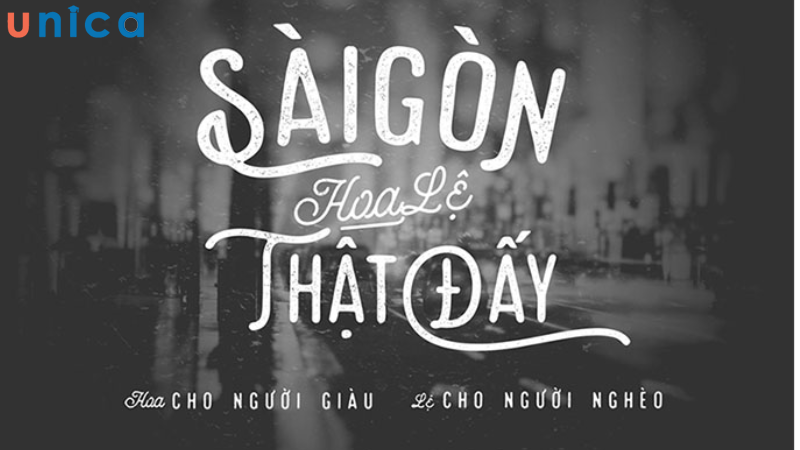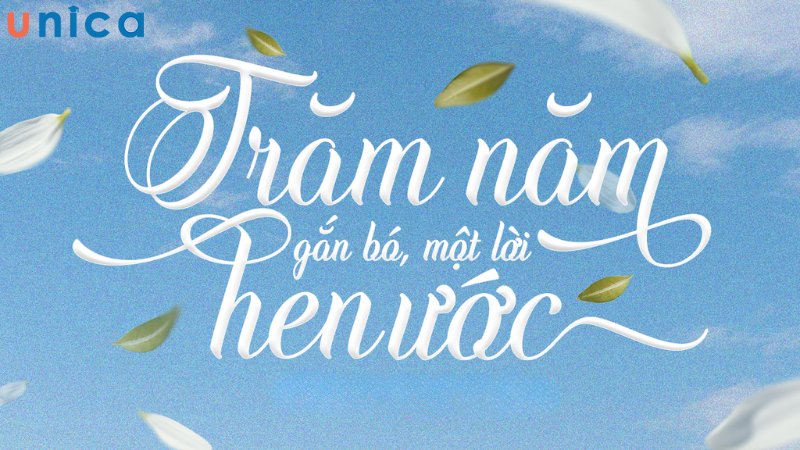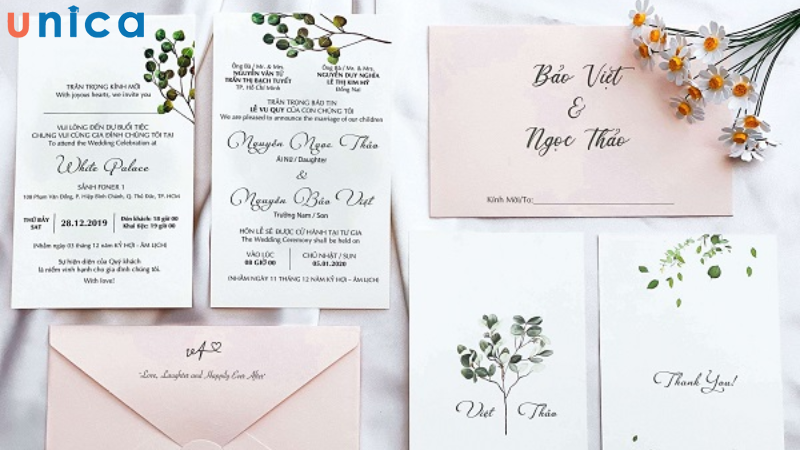
Top 30+ Font chữ viết tay Việt hóa cho người làm thiết kế
Việc sử dụng các font mặc định để viết chữ trong phần mềm Photoshop sẽ làm cho những designer bị gò bó và thiếu đi sự sáng tạo. Vậy làm thế nào để các designer có thể tự tạo nên những Font chữ Việt hóa theo mong muốn của mình. Sau đây, Unica sẽ gửi đến các bạn Top 5 Font chữ viết tay Việt hóa đẹp nhất mà không phải ai cũng biết.
Font chữ việt hóa viết tay là gì?
Font chữ viết tay Việt hóa là những bộ font đã được điều chỉnh và tối ưu hóa để hỗ trợ đầy đủ các ký tự trong tiếng Việt. Những bộ font này thường được sử dụng trong các thiết kế đồ họa như thiệp mời, thiệp chúc mừng, hay các ấn phẩm quảng cáo. Việc sử dụng các font viết tay giúp thay đổi diện mạo thiết kế, mang đến nét độc đáo và sự khác biệt nhờ vào sự đa dạng của các kiểu chữ.
Font chữ viết tay mang đến nhiều lợi ích thiết thực cho người dùng, đặc biệt trong các hoạt động sáng tạo và thiết kế. So với việc sử dụng các font chữ thông thường, bộ font này không chỉ đa dạng hơn mà còn truyền tải được cảm xúc và phong cách riêng biệt.
Font chữ viết tay Việt hóa là những font chữ đã được tối ưu khi soạn thảo bằng tiếng Việt
Về cơ bản, font chữ viết tay (hay còn gọi là Typography) là các kiểu chữ được hiển thị trên màn hình máy tính theo phong cách viết tay tự nhiên. Một số bộ font được Việt hóa hoàn chỉnh để phù hợp với tiếng Việt, trong khi các bộ khác được tạo ra theo phong cách nghệ thuật, mang đậm dấu ấn thiết kế.
Những bộ font chữ viết tay Việt hóa được các nhà thiết kế đồ họa ưa chuộng trong nhiều ứng dụng như thiết kế thiệp cưới, thiệp chúc mừng, poster quảng cáo, chỉnh sửa hình ảnh và truyền thông marketing. Chúng góp phần tạo nên điểm nhấn riêng và giúp các sản phẩm thiết kế trở nên bắt mắt, cuốn hút hơn.
Tương tự, trong lĩnh vực giáo dục, các giáo viên bậc tiểu học thường sử dụng font chữ viết tay để giúp học sinh luyện viết chữ. Điều này khác biệt hoàn toàn so với những font chữ cơ bản như Arial hay Times New Roman, vốn không thể hiện được cảm xúc và sự tinh tế qua từng con chữ. Những bộ font viết tay không chỉ mang lại sự trang trọng, mà còn truyền tải thông điệp rõ ràng và hiệu quả hơn trong mọi trường hợp.
Lý do nên sử dụng font chữ viết tay Việt hóa?
Font chữ viết tay Việt hóa được thiết kế với những đường nét tinh tế, mềm mại và được tối ưu hóa dành riêng cho người dùng Việt Nam. So với font chữ đánh máy thông thường, các bộ font này mang đến sự thân thiện và gần gũi, tạo ấn tượng mạnh mẽ cho người xem.
Bên cạnh đó, font chữ viết tay Việt hóa còn thể hiện rõ nét cá tính và sự sáng tạo trong từng thiết kế. Với sự đa dạng về kiểu dáng, kích thước và phong cách, bạn hoàn toàn có thể lựa chọn font chữ phù hợp với từng mục đích cụ thể. Nếu bạn yêu thích sự cổ điển và sang trọng, những font chữ có đường nét uốn lượn, mềm mại sẽ là lựa chọn hoàn hảo. Ngược lại, nếu bạn theo đuổi phong cách hiện đại và mạnh mẽ, các font chữ với đường nét dứt khoát và khỏe khoắn sẽ giúp truyền tải thông điệp rõ ràng hơn.
Sử dụng font chữ Việt hóa có sự tinh tế, mềm mại và được tối ưu cho người Việt
Khi nào nên sử dụng font chữ viết tay Việt hóa?
Thiết kế thiệp cưới, thiệp chúc mừng
Một trong những ưu điểm nổi bật của font chữ viết tay Việt hóa chính là khả năng truyền tải cảm xúc chân thành đến người đọc. Chính vì điều này, font chữ viết tay thường được sử dụng rộng rãi trong việc thiết kế các tấm thiệp cưới, thiệp chúc mừng hay các ấn phẩm nhỏ mang tính cá nhân hóa cao.
Thiết kế các ấn phẩm truyền thông Marketing
Trong các chiến dịch truyền thông và marketing, font chữ viết tay Việt hóa giúp cho thông điệp của bạn trở nên sinh động và gần gũi hơn với đối tượng mục tiêu. Với khả năng tạo hiệu ứng thị giác mạnh mẽ, những bộ font này không chỉ thu hút sự chú ý mà còn để lại ấn tượng sâu sắc trong tâm trí khách hàng.
Thiết kế nhận diện thương hiệu
Font chữ viết tay Việt hóa đóng vai trò quan trọng trong việc thiết kế logo, banner, poster và các ấn phẩm nhận diện thương hiệu khác. Nhờ vào sự độc đáo và linh hoạt của mình, font chữ viết tay giúp thương hiệu trở nên nổi bật hơn, dễ dàng ghi nhớ và tạo cảm giác thân thiện đối với khách hàng.
Font chữ Việt hóa thường hay được sử dụng trong thiệp cưới, thiệp mời
Top 30+ font chữ Việt hóa được sử dụng nhiều nhất
Font SVN-Museo Sans
Museo là Font chữ Việt hóa đẹp được xây dựng dựa trên nhiều yếu tố hình học, dễ đọc và phù hợp với nhiều loại sản phẩm từ online cho đến các ấn phẩm in. Mẫu font này được thiết kế bởi Jos Buivenga.
Kết luận
Với tổng hợp 30+ font chữ Việt hóa được giới thiệu ở trên, bạn đã có thêm nhiều lựa chọn tuyệt vời để làm mới các thiết kế và tài liệu của mình. Những font chữ này không chỉ mang đến vẻ đẹp mềm mại, tự nhiên mà còn đảm bảo tính thẩm mỹ và dễ dàng tích hợp trên các phần mềm như Word, Photoshop, Illustrator. Hy vọng bài viết đã cung cấp cho bạn những thông tin hữu ích, phục vụ công việc của bạn.